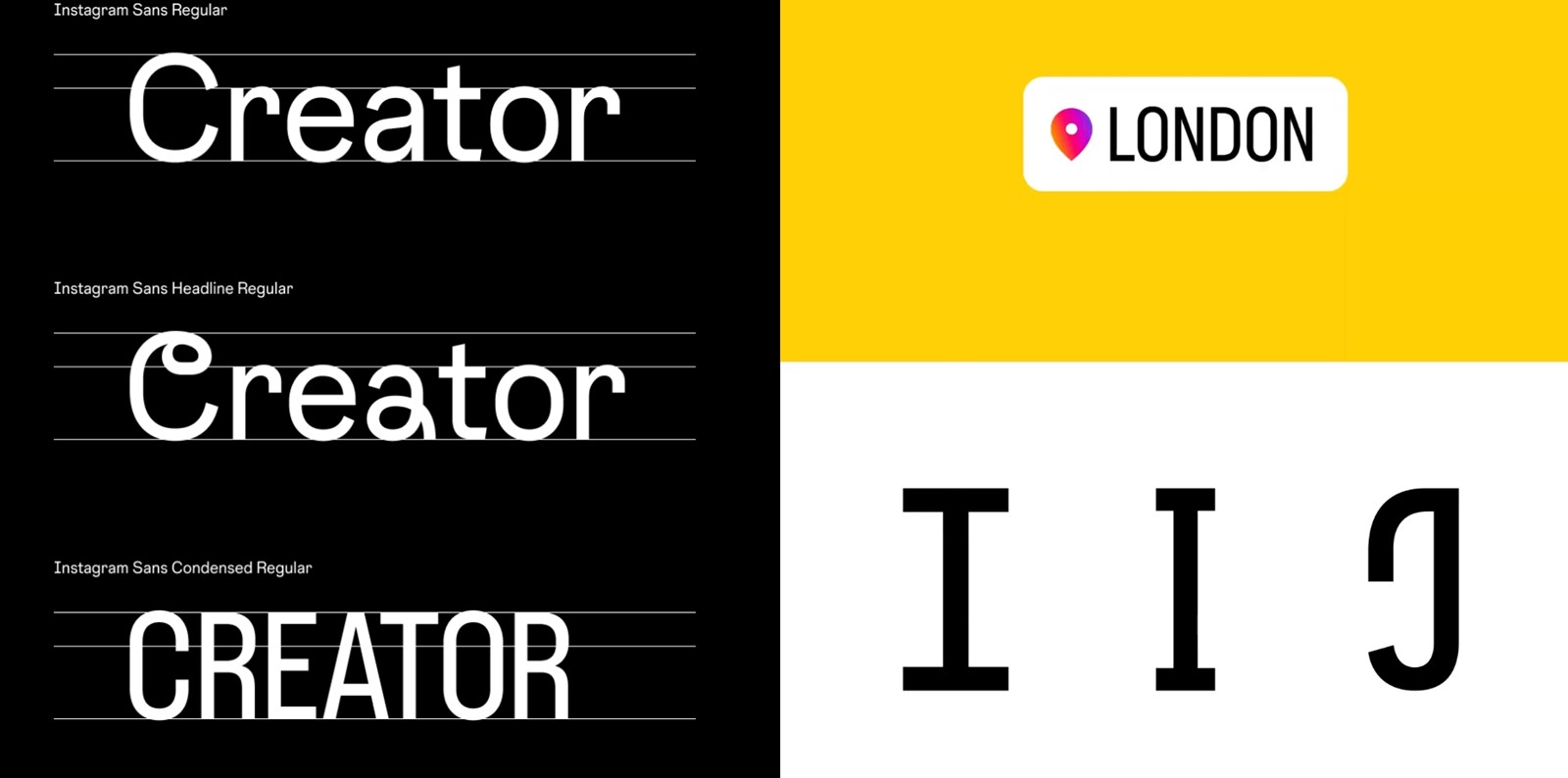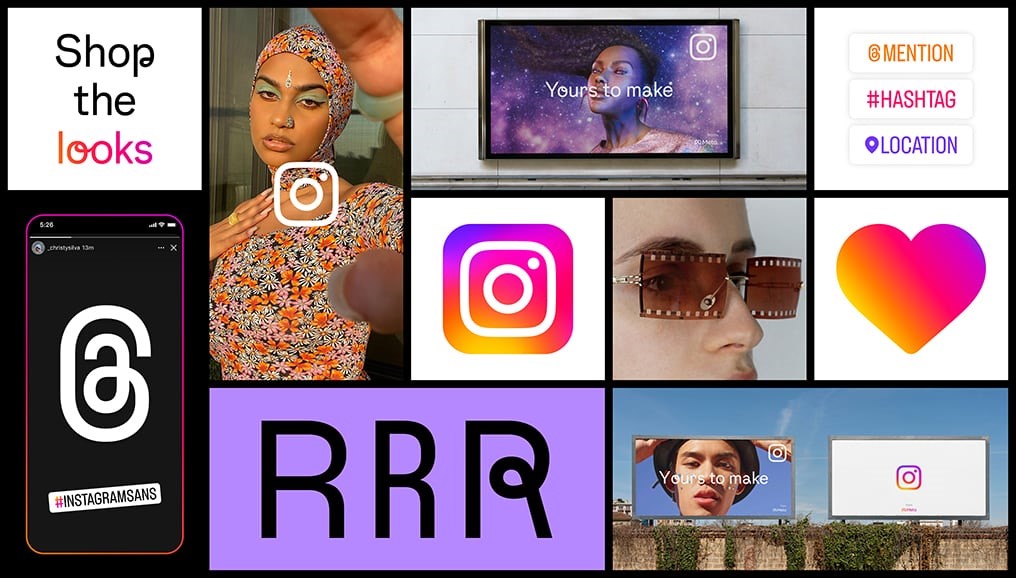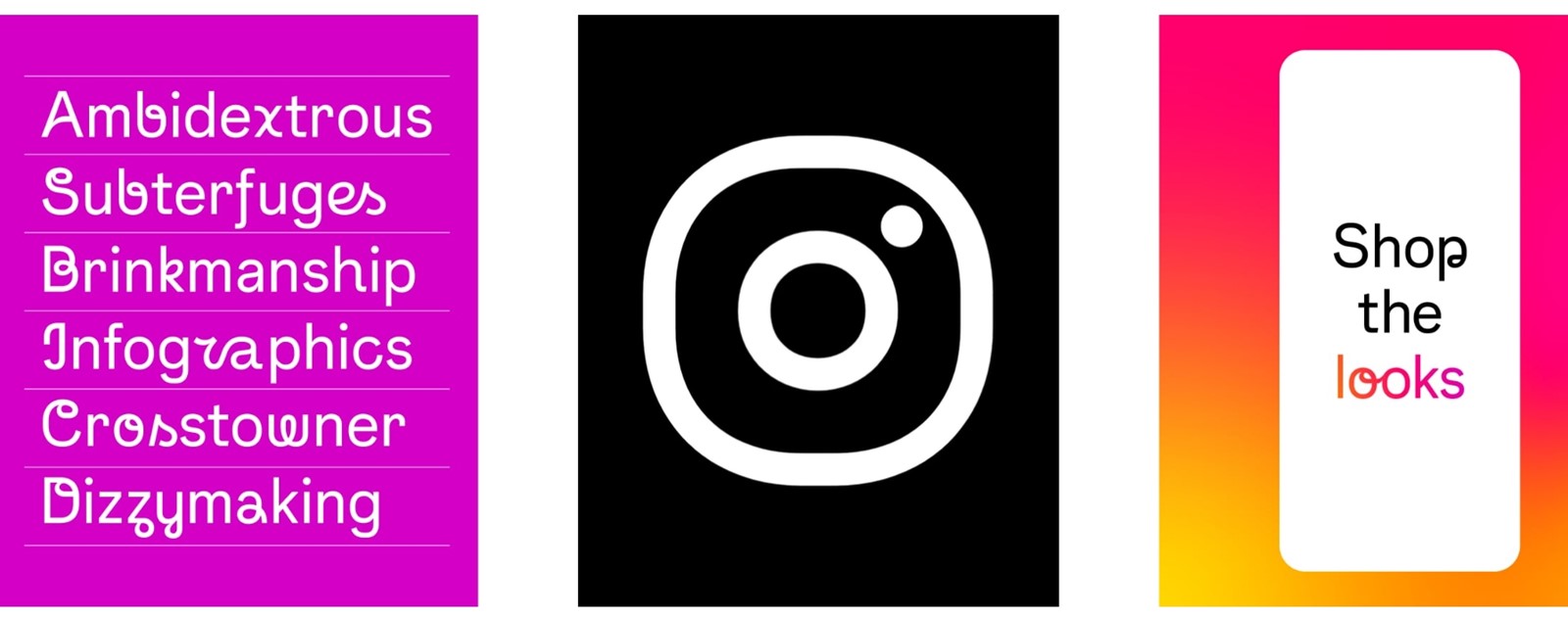
Instagram osvježio dizajn i predstavio vlastiti novi font
Novi vizualni identitet Instagrama neće toliko utjecati na samu društvenu mrežu i korisnike, koliko na njezinu marketinšku komunikaciju. Pritom će poruke biti ispisivane novim, zanimljivim, fontom
Instagram, društvena mreža koja diktira mnoge trendove u svijetu dizajna, mode, influencera i srodnih grana, otkrila je svoj novi vizualni identitet. I dalje je on "mladenački", svjež, jednostavan, razigran i šarolik, ali od sada sa sobom nosi određene nove elemente koji "donose novu energiju", kako kažu njihovi dizajneri.
Prepoznatljivo prelijevanje boja, koje često služi kao pozadina i krasi ikonu Instagrama, od sada će biti nešto vedrije i svjetlije. Dizajn će općenito biti više fokusiran na sadržaj, odnosno velike slike uz tek minimalne količine teksta – a taj će tekst biti ispisan novim fontom.
Instagram Sans
Kako bi se još više istaknuli i naglasili svoj identitet, u Instagramu su odlučili stvoriti font kojim će se oglašavati i ispisivati sve svoje marketinške poruke. Njegovo ime je Instagram Sans, a opis kaže da je to "font budućnosti izgrađen na prošlosti".
Dolazit će u tri varijante – običnoj, bezserifnoj, nazvanoj Regulari i sličnoj fontovima kao što su Roboto, Calibri ili Verdana. Druga inačica naziva se Headline Regular, a zamišljena je kao ukrasni font kojim će se ispisivati tek naslovi ili istaknuti dijelovi teksta. Ova verzija donosi zanimljive lukove, ligature i poneku neobičnu krivulju koja naglašava pojedina slova te tako privlači pozornost.
Treća je Condensed varijanta, za posebne namjene, kada je u što manje prostora potrebno "ugurati" što više teksta.
Novim fontovima bit će ispisivano Instagramovo ime, tekstovi na oglasima i internetskim stranicama, kako na latinici tako i na svim drugim pismima u svijetu, uključujući arapska, japanska ili ćirilična.